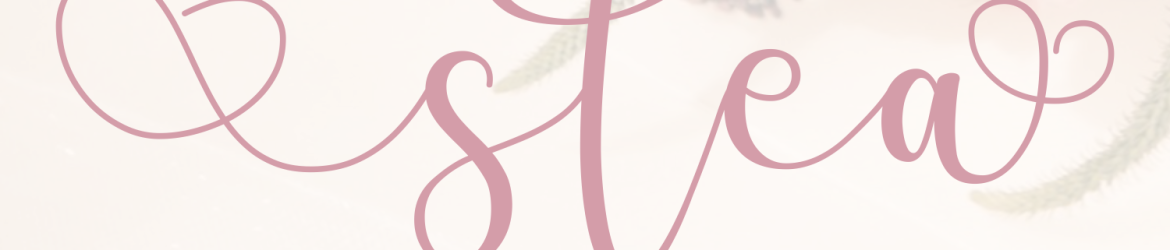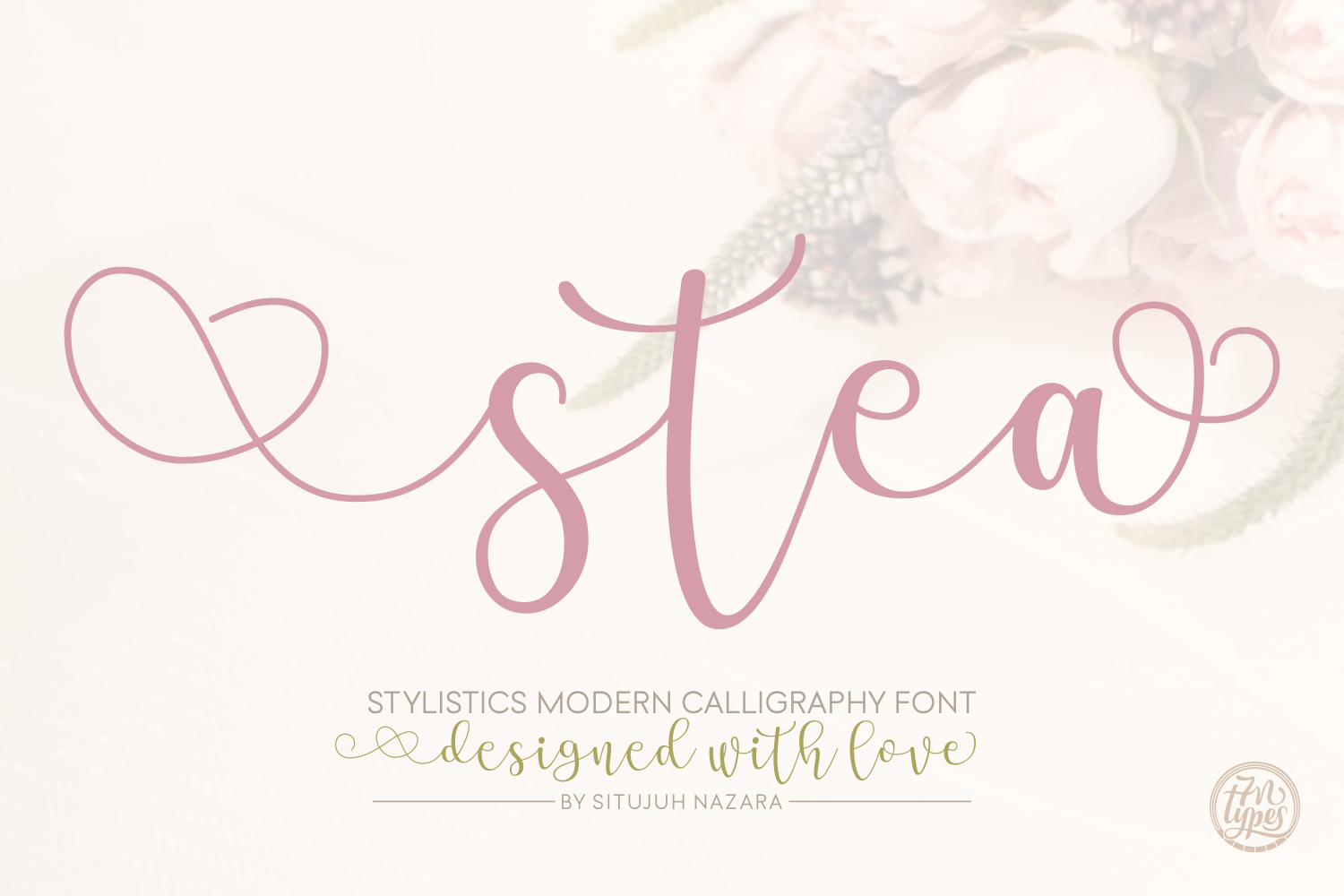
Stea Calligraphy Font – Fonte Grátis
Stea Calligraphy Font
Aqui está uma descrição envolvente e natural para a Stea Calligraphy Font: Estamos muito felizes por poder apresentar à vocês uma nova opção incrível em nosso catálogo de fontes, uma que combina sofisticação com charme na medida certa. A Stea Calligraphy Font, criada pelo talentoso designer Hamilton, é perfeitamente adequada para aqueles que buscam um touch especial em seus trabalhos. A Stea não apenas oferece estilo moderno e elegante, mas também uma característica única que torna a escrita de texto muito mais encantadora. Esta fonte vem equipada com caracteres decorativos que podem ser usados tanto nas extremidades dos termos quanto para ligar palavras juntas, criando uma série de combinações únicas e inovadoras. O design da Stea foi pensado para torná-la acessível a todos os usuários. Se você estiver trabalhando em projetos que requerem elementos decorativos, pode usar números como bordas ou padrões em suas criações. Esta fonte é ideal tanto para designers de layout quanto para aqueles que desejam dar um toque especial a texturas e gráficos. Com Stea Calligraphy Font, adicionar um toque único ao seu trabalho de design torna-se uma tarefa fácil e divertida. E como não poderíamos deixar de mencionar, esta fonte é certamente uma peça de destaque no seu portfólio gráfico.